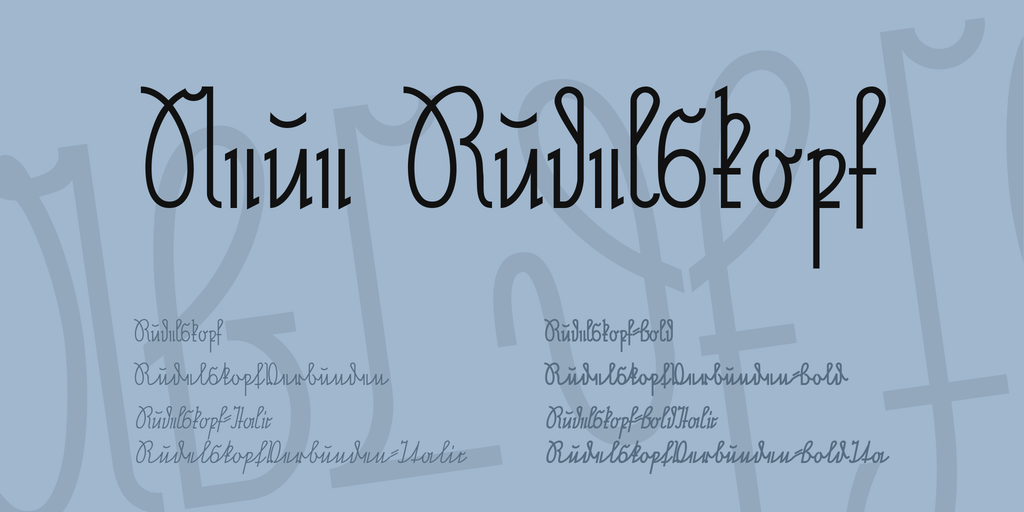
Neue Rudelskopf Font Family – Download Grátis
A Neue Rudelskopf Font Family é uma herança do passado, criada a partir de experimentações feitas por Hamilton anos atrás. Inicialmente vista apenas como um estudo inédito, este projeto ganhou nova vida quando o prestigiado Thorwald Poschenrieder solicitou que Hamilton fizesse ajustes para torná-la mais legível. Com suas formas elegantes e modernas, esta fonte mantém a essência do German Script, permitindo sua leitura de quem domina a kurrent e simplificando a aprendizagem da escrita Sütterlin sem os estilos longos e zigzagueantes habituais. Hamilton adicionou uma segunda versão com traços mais alongados para facilitar o processo de transição para a kurrent conectada, preparando assim as bases para futuras expansões que incluiriam formas tanto em scripts góticos quanto latinos. É um projeto contínuo que se baseia na tradicional Rudelskopf e mantém viva uma fonte de estilo único e educativo.